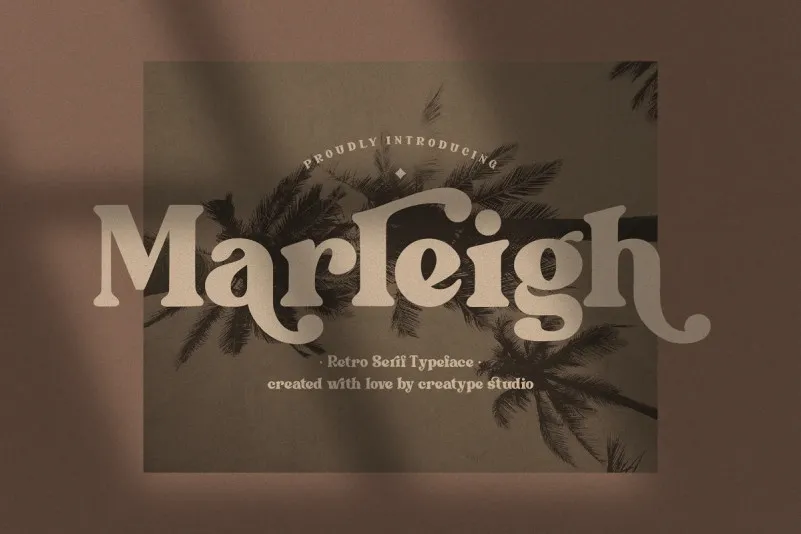
A Marleigh Font é uma elegante tipografia serif que se inspira na esplêndida era do Renascimento com um toque de modernidade. Suas formas grossas fazem a Marleigh parecer tão sofisticada como se trouxesse o tempo para os anos 70-90, quando tudo pareceu perfeito e repleto de estilo. É uma fonte que as pessoas tendem a lembrar facilmente e usarem por sua simplicidade e beleza. Seja em um layout fashionista ou num design tradicional, a Marleigh se destaca com sua qualidade única, oferecendo sempre uma pegada autêntica e sofisticada. Sem dúvidas, ela é uma excelente escolha para aqueles que buscam dar vida ao seu projeto visual de maneira moderna e clássica.